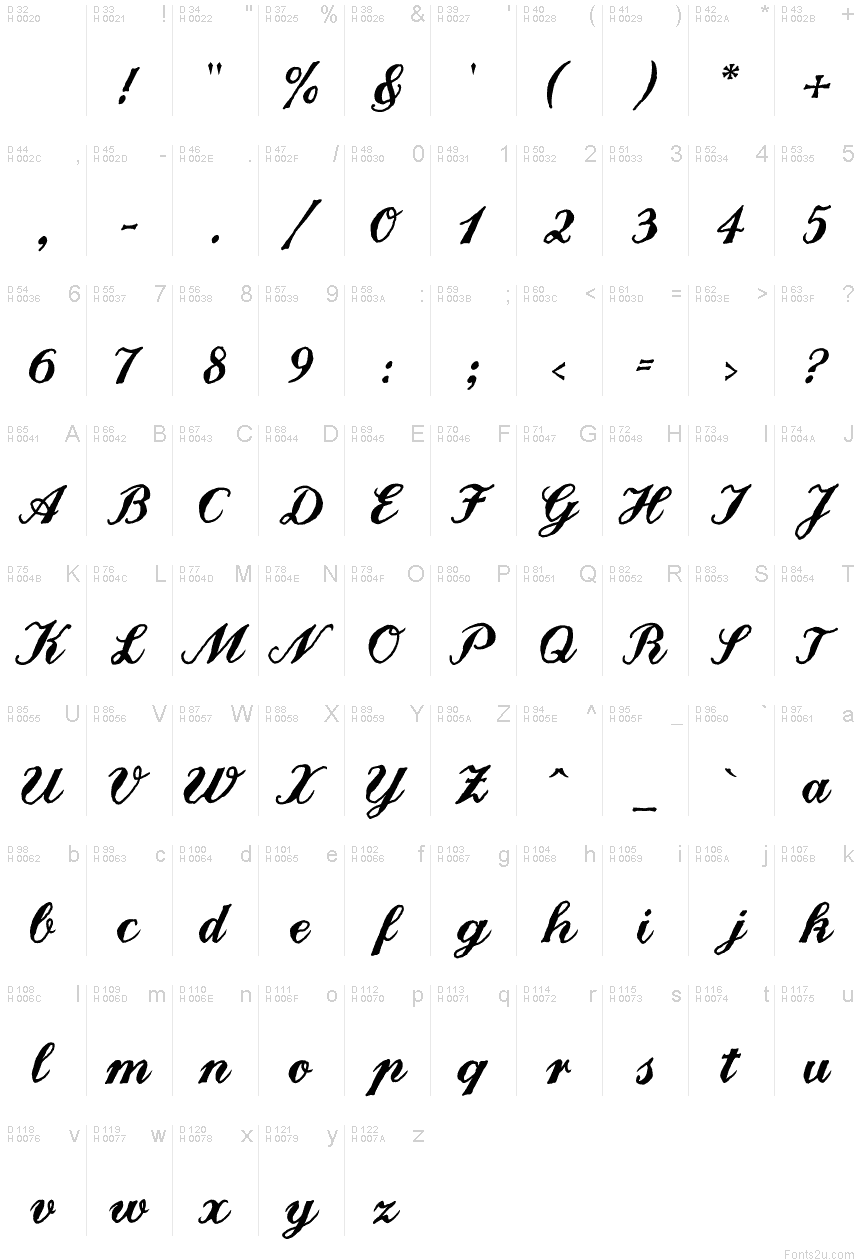
Landliebe autorstwa Richarda Mitchella (Underground Grammarian) to darmowy krój pisma odręcznego o płynnych, połączonych liniach. Pętlowy kształt nadaje literom rytm, jakby były kreślone ręcznie. Formy są lekko zaokrąglone i swobodne, z długimi, miękkimi łączeniami, dzięki czemu linia jest dynamiczna i pozbawiona sztywności.
Landliebe świetnie sprawdza się w zaproszeniach ślubnych, kartkach okolicznościowych, logotypach, opakowaniach produktów, grafikach z cytatami i identyfikacji wizualnej kawiarni, ponieważ jego kursywny rytm nadaje krótkim tekstom osobisty, pisany charakter. Ten darmowy font jest również idealny do nagłówków w mediach społecznościowych, papeterii czy podpisów, gdy zależy Ci na napisach, które sprawiają wrażenie nieformalnych i autentycznych, a nie mechanicznych.
Made by Richard Mitchell, the Underground Grammarian.
Landliebe